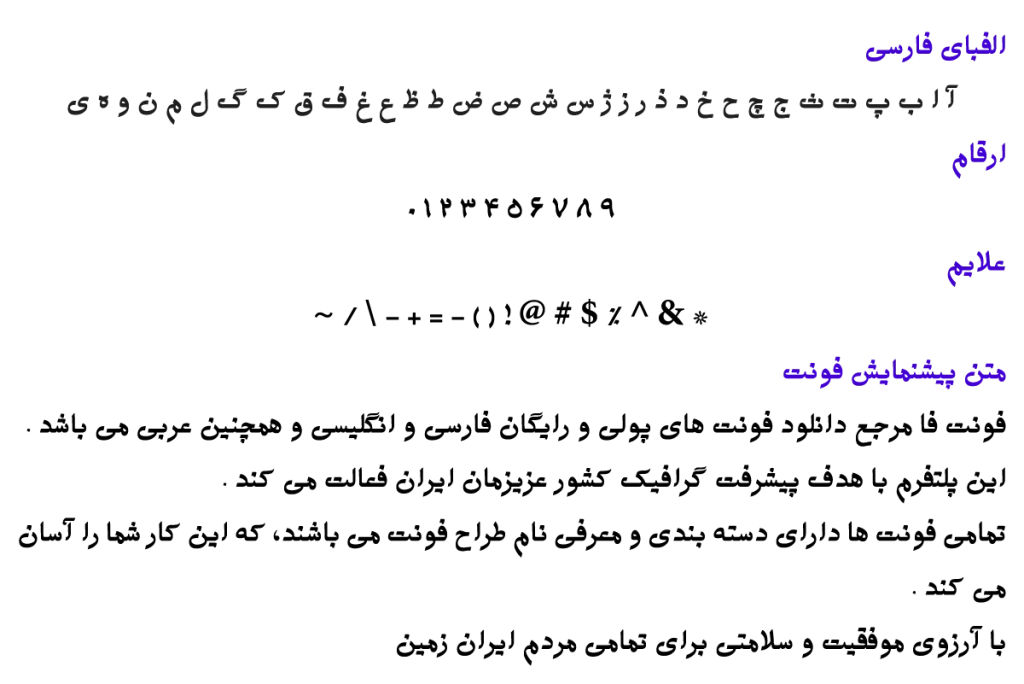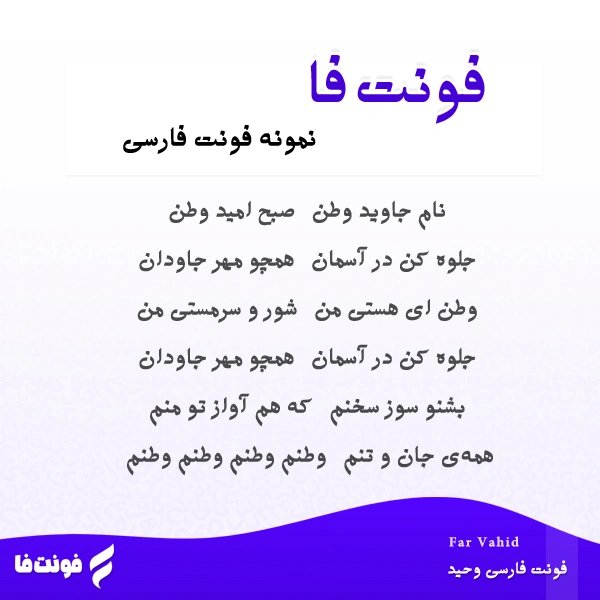
فونت فارسی وحید – Far Vahid
مجموعه فونت: فونت سری Far
طراح فونت: ابوالفضل سيل سپور نوع فونت: فونت گرافیکی
پیشنمایش فونت وحید
توضیحات و معرفی فونت وحید
فونت فارسی وحید ( Far Vahid ) از مجموعه فونت های سری Far می باشد، و نیز نوع فونت گرافیکی می باشد.
فونت خوشگل مربوط توسط ابوالفضل سيل سپور در سال 1390 طراحی و ساخته شده است.
و نیز فونت Far Vahid در یک وزن پر رنگ است.
- Far Vahid Bold
شعر میهنی زیر با این تایپ فیس طراحی شده و نمایانگر زیبایی آن است.